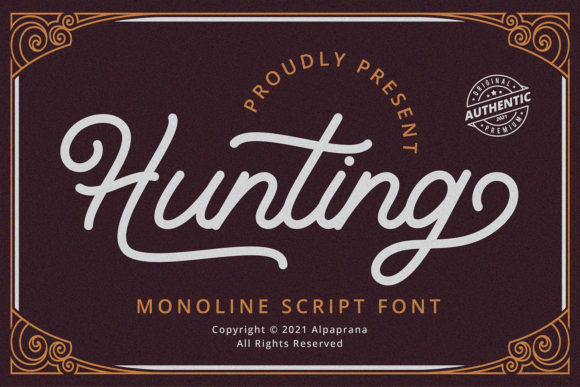
Creativefabrica Hunting Font
[Creativefabrica] Hunting Font
Охота - это красивый легкий рукописный шрифт с уникальными ощущениями и потрясающим эффектом.
Он добавит роскошной искры в любой дизайн-проект, который вы хотите создать!